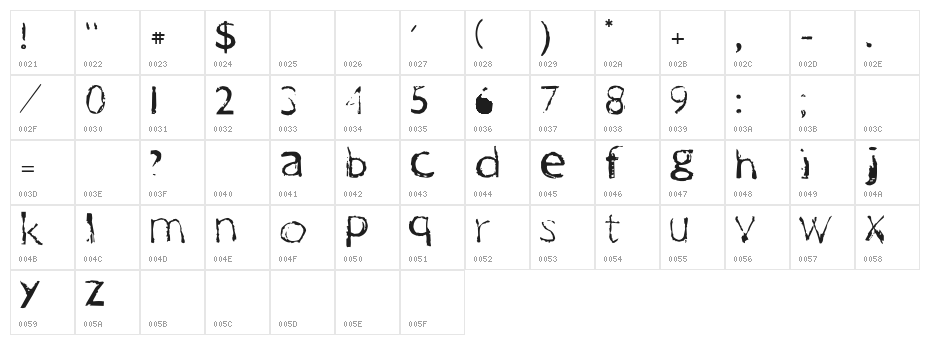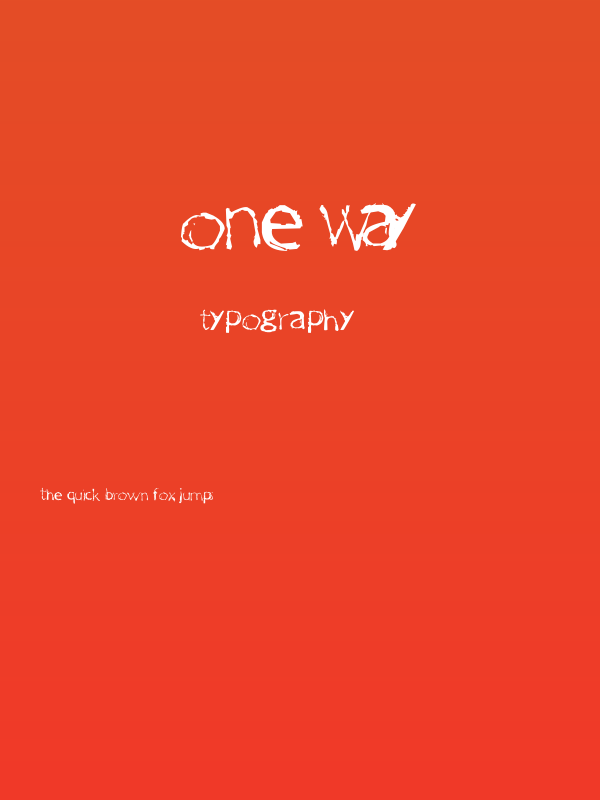
One Way Font
| Style général | Grunge, Edgy, Raw |
| Cas d'utilisation | Logos, Posters, Album Covers |
| Projets proposés | Ideal for music album covers, streetwear branding, skateboarding graphics, or any project seeking an edgy, rebellious vibe. |